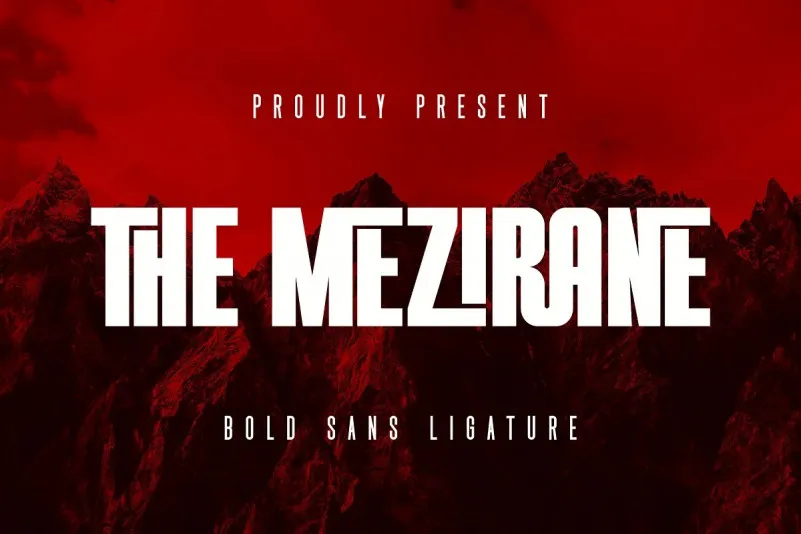
THE MEZIRANE Font – Download Grátis
A MEZIRANE é uma fonte sans-serif moderna projetada pela Almarkha Type, inspirada no título de uma campanha esportiva. Ela captura a energia e dinamismo dessas artefatos visuais com uma atenção meticulosa aos detalhes gráficos, como o peso e densidade dos glífos. Uma característica singular desta fonte é sua ligação que contribui para sua unicidade única, tornando-a um recurso visual inigualável. Essa fonte não apenas reforça a identidade do design, mas também oferece uma maneira vívida de expressar diferentes estilos e ambientes gráficos, tornando-se uma escolha perfeita tanto para criações de apresentação quanto para textos em seletivas áreas como blogs ou sites.